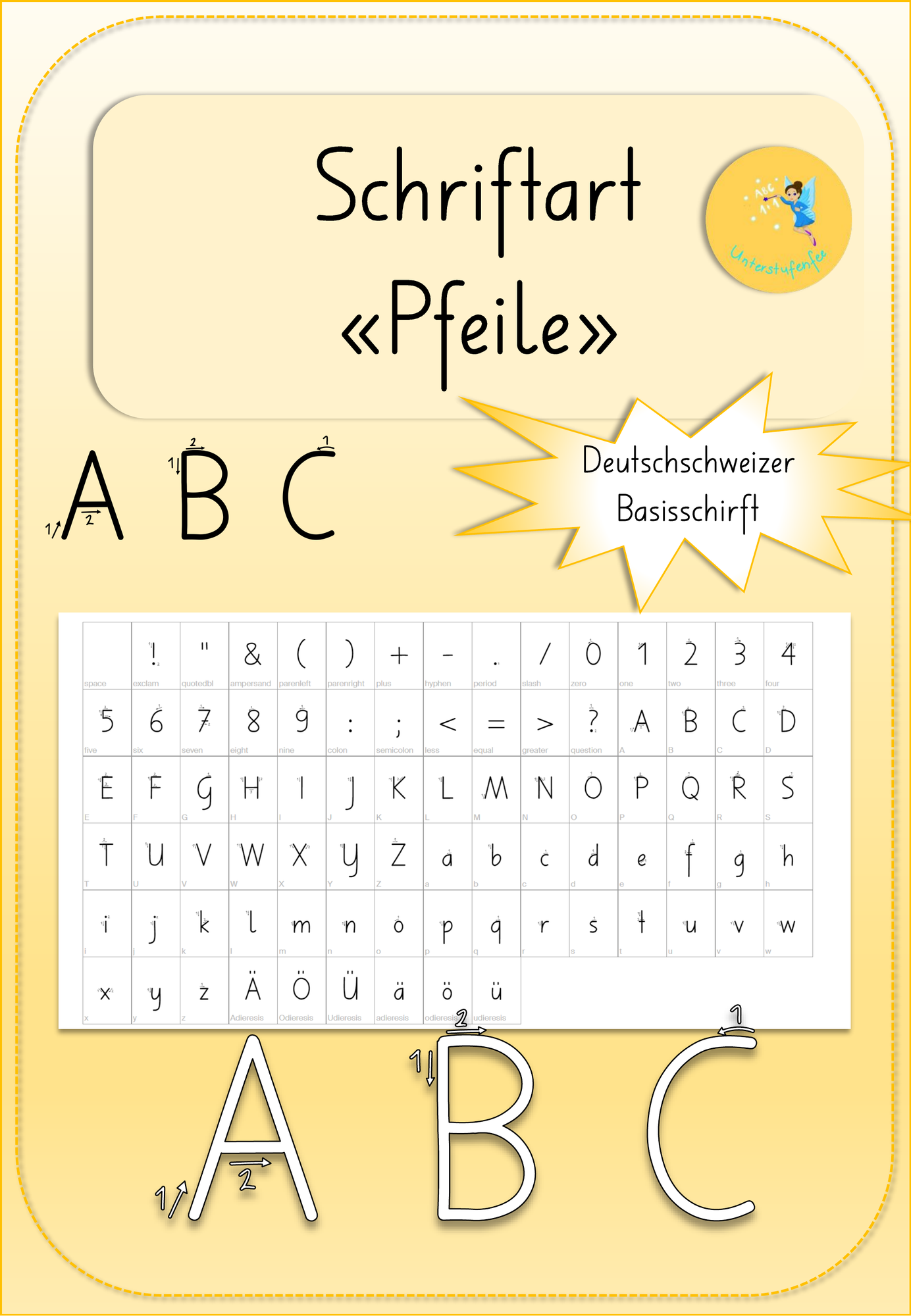
selbst erstellte Schriftarten - Deutschschweizer Basisschrift mit Pfeilen (Schriftart) - Unterstufenfee - Deckblatt
Bei diesem Material handelt es sich um eine selbsterstellte Schriftart. Es ist die deutschschweizer Basisschrift mit Pfeilen, die den korrekten Schreibablauf angeben. Die Schriftart kann genutzt werden, um Arbeitsblätter und Materialien mit Schriften zum Nachspuren zu versehen.
Deutschschweizer Basisschrift mit Pfeilen (Schriftart)